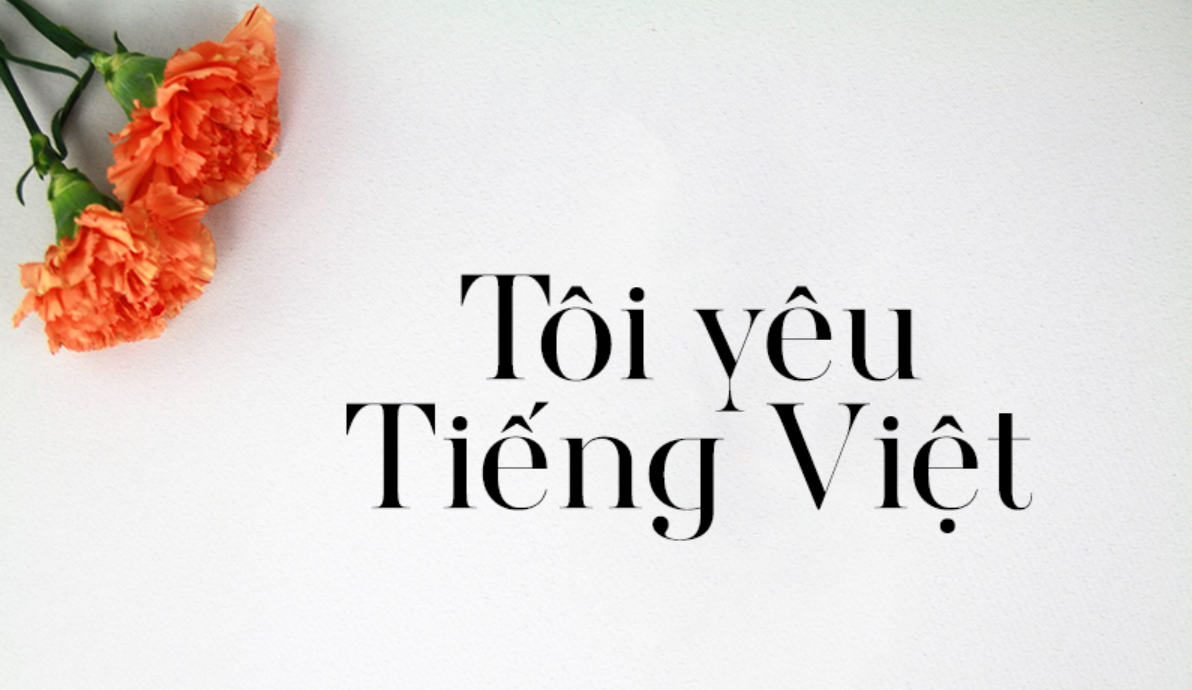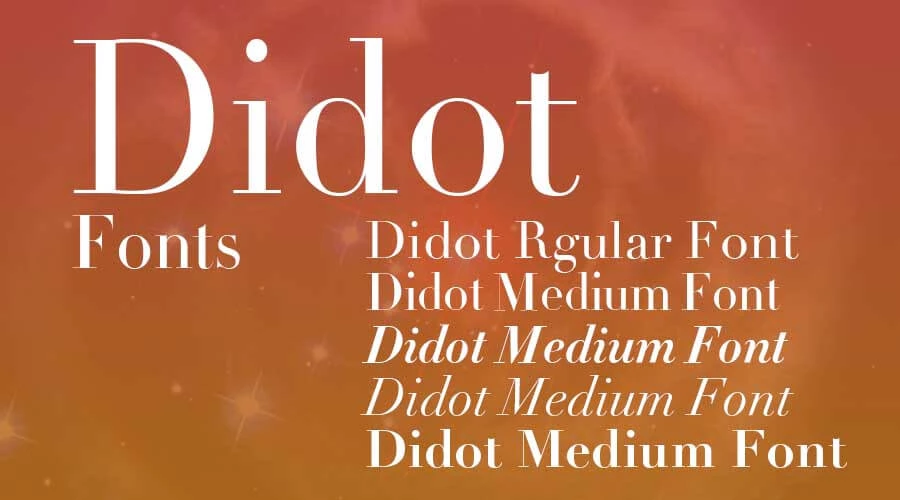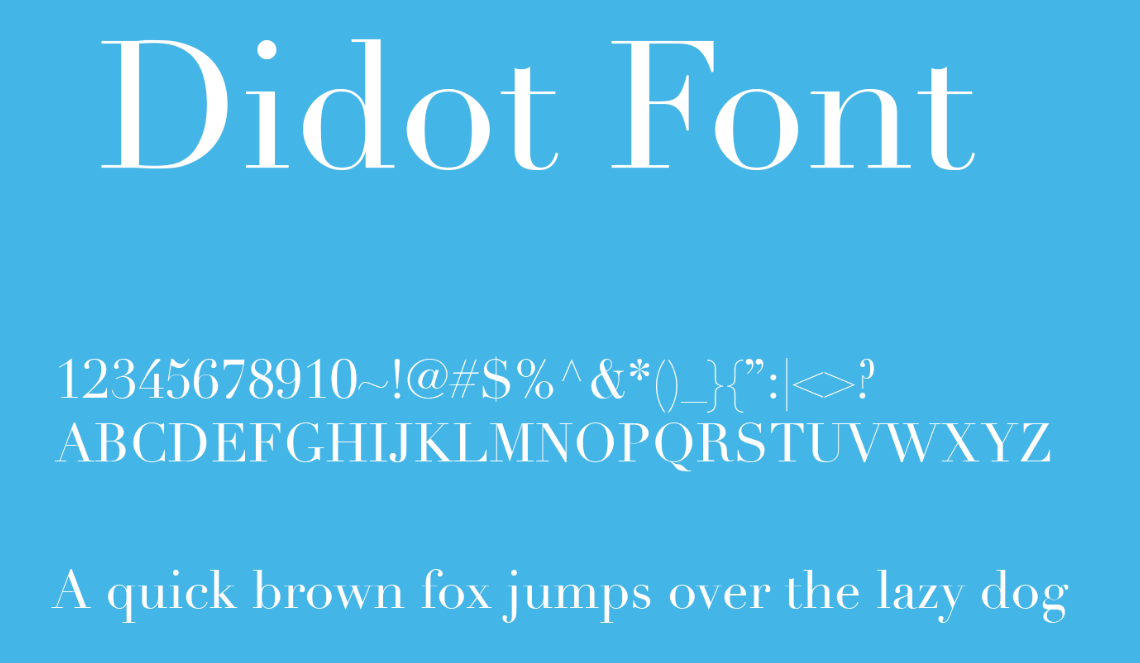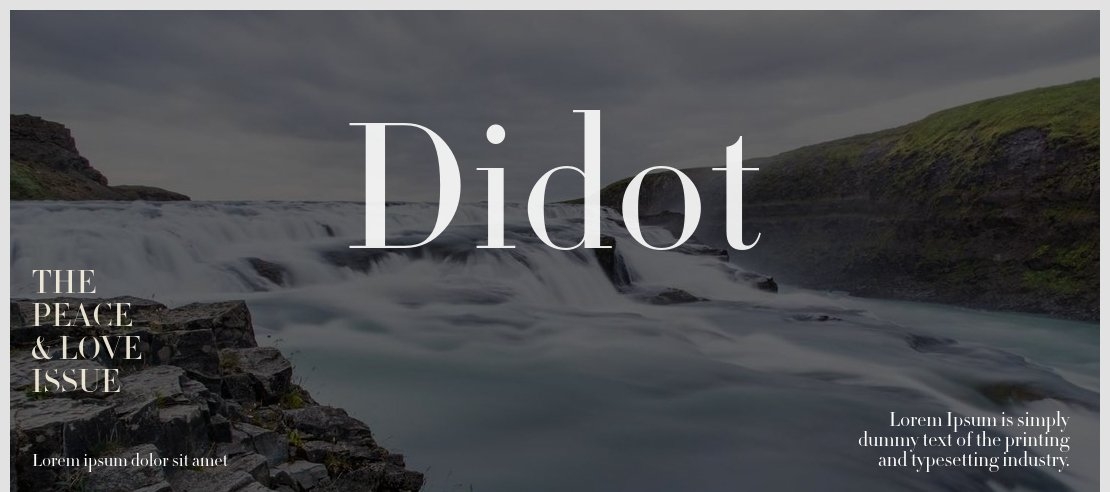
Font UVF Didot là bộ phông chữ có chân (Serif) mang tính biểu tượng vĩnh cửu của ngành thời trang cao cấp và đồ họa xa xỉ, được sáng tạo ban đầu bởi Firmin Didot tại Paris vào cuối thế kỷ 18. Với độ tương phản nét thanh đậm sắc sảo bậc nhất cùng chân chữ phẳng dứt khoát, Didot là biểu tượng nhận diện của các tạp chí danh giá như Vogue, Harper’s Bazaar và các thương hiệu nước hoa hàng đầu thế giới. Doozypack.vn chia sẻ link tải font UVF Didot chuẩn kỹ thuật, giúp bạn sở hữu phông chữ đẳng cấp hoàng gia mà không lo gặp bất kỳ lỗi hiển thị dấu thanh nào khi thiết kế bao bì.
Đặc điểm thẩm mỹ độc đáo của Font UVF Didot
Didot đại diện cho đỉnh cao của trường phái Typography Didone, nơi tính kỷ luật hình học và sự xa hoa của thời trang hòa quyện làm một.
Phong cách Modern Serif với độ tương phản nét thanh đậm tột đỉnh
Đặc trưng lớn nhất của Font UVF Didot là sự đối lập mãnh liệt giữa các nét dọc dày dặn, vững chãi và các nét ngang thanh mảnh như sợi tơ (hairline). Cấu trúc chữ sở hữu trục thẳng đứng tuyệt đối, các đường cong mở rộng kiêu sa tạo nên một nhịp điệu thị giác vô cùng lôi cuốn. Khi đặt Didot làm tiêu đề trên bao bì, sản phẩm của bạn sẽ ngay lập tức toát lên diện mạo quý tộc, đắt tiền và mang đậm tinh thần thẩm mỹ Paris thời thượng.
Chân chữ phẳng và sắc sảo chuẩn mực Paris
Khác với các dòng phông chữ có chân cổ điển với phần góc chân chữ bo cong mềm, Didot sở hữu phần chân chữ (serif) hoàn toàn phẳng và thanh mảnh. Chi tiết này mang lại vẻ ngoài gọn gàng, sắc lẹm và cực kỳ tinh tế, giúp các dòng tiêu đề trên vỏ hộp giữ được sự thanh thoát, kiêu kỳ mà không hề tạo cảm giác nặng nề.
Ưu điểm nổi bật của bản font Didot Việt hóa trong thiết kế
Khi ứng dụng các phông chữ có độ tương phản cao vào thị trường trong nước, sự chỉn chu về dấu câu là yếu tố quyết định đến tính chuyên nghiệp của bản thiết kế:
- Khắc phục triệt để lỗi dấu tiếng Việt: Phiên bản font Didot Việt hóa thuộc hệ thống UVF đã được các chuyên gia tinh chỉnh thủ công từng dấu câu. Các dấu sắc, huyền, hỏi, ngã, nặng được thiết kế thanh mảnh đồng nhất cùng thân chữ gốc, không gây cảm giác chắp vá hay đè nét làm mất tính thẩm mỹ.
- Bảo đảm tính đồng nhất thương hiệu: Việc tải font Didot chuẩn giúp bạn tự tin dàn trang tiêu đề tiếng Việt mà không lo hiện tượng lỗi ô vuông hay nhảy về font hệ thống khô khan.
- Hộp giấy đựng Nước hoa & Mỹ phẩm Luxury: Tiêu đề thương hiệu in bằng font Didot kết hợp kỹ thuật ép kim nhũ vàng trên giấy Ivory cán màng mờ tạo nên vẻ đẹp sang trọng chuẩn phong cách thời trang cao cấp.
- Túi giấy thời trang cao cấp: Tên cửa hàng in bằng font Didot màu đen tối giản trên nền túi giấy trắng giúp khẳng định gu thẩm mỹ tinh tế của nhãn hàng trong mắt người tiêu dùng.
- Nhãn dán chai Rượu vang & Nến thơm: Nét chữ Serif sắc sảo mang lại cảm giác thư giãn, sạch sẽ và thượng lưu cho các dòng sản phẩm quà tặng tinh tế.